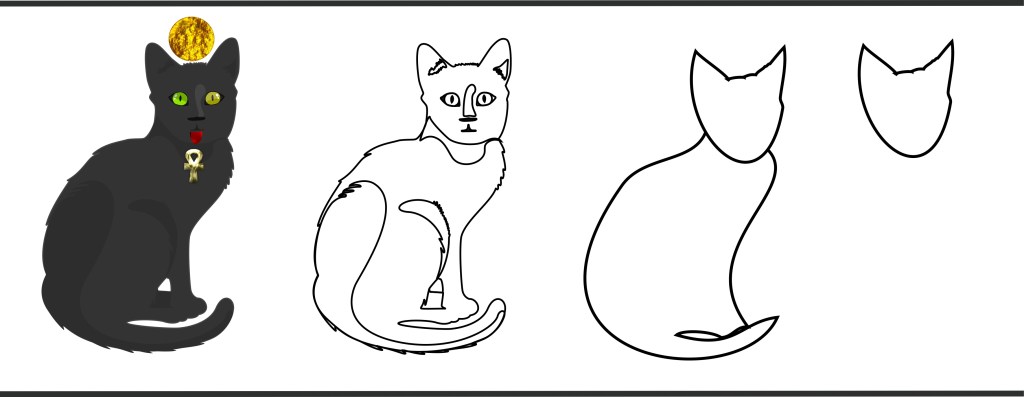
Écrire en dessinant ? Rien de plus facile !
L’écriture Hiéroglyphique est, pour une bonne part, la constitution d’un message sous la forme de rébus, des successions de graphismes expriment les objets, les personnes, les animaux, la flore, les situations.
Les traits, les formes, les dessins ne sont que rarement les choses représentées mais leurs prononciations. Celles-ci sont conditionnées par des signes de ponctuation.
En dessinant, il est possible de mélanger les graphismes explicites et non explicites, tels que des représentations de divinités avec des signes triviaux, indicatifs de sens.
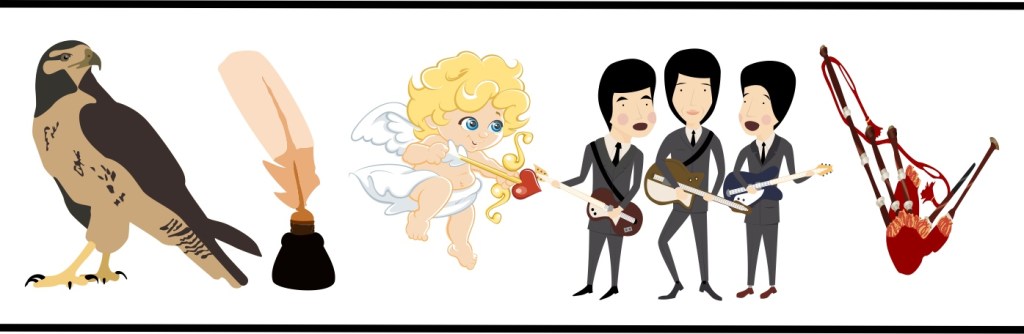
Ainsi, si l’on fait figurer une image d’oiseau, un faucon, l’emblème de Rà, cela peut vouloir dire beaucoup de choses.
Faucon, écrire, romance, groupe, cornemuse.
Cela se lit de gauche à droite car le faucon regarde vers la droite. A priori, c’est facile à comprendre : un producteur veut travailler sur une chanson d’amour avec son parolier, tout en lui précisant habilement que les interprètes sont des guitaristes. Ici, les syllabes de « faucon » sont utilisées pour leurs sonorités et non leurs sens graphiques, il faut les entendre pour comprendre, ce qui est assez facile.
Et pour la cornemuse ? Est-elle présente parce que les guitaristes sont de Glasgow ?
Là où cela se complique.
On lira dans ce cas : Faut qu’on écrive de l’amour pour le trio des chanteurs Écossais. Toutefois, la cornemuse peut aussi être là pour ses sonorités. Il convient de remplacer Écossais par la performance vocale du trio
On comprend : Faut qu’on écrive une chanson d’amour pour les guitaristes qui couinent. L’auteur du message considère qu’ils chantent trop haut.
Comme si cela ne suffisait pas, une autre interprétation se propose, celle qui implique la nature de la cornemuse, dans laquelle on souffle afin de la presser pour en faire sortir l’air.
Le sens est alors quelque peu différent : Faut qu’on écrive une chanson d’amour pour ce trio qui me gonfle et me pressure.
Le rédacteur exprime son agacement envers ses musiciens, très insistants et dont le montant du cachet lui semble exagéré. Ce qui induit que c’est bien un producteur qui écrit.
On ne peut pas exclure que les trois sens se superposent, les musiciens sont Écossais, près de leurs sous, avides de nouveaux succès et chantent dans les aiguës.
Le recours aux noms d’oiseaux.
L’interprétation des hiéroglyphes n’est pas toujours facile. Aussi, il est important d’ajouter des indicateurs de compréhension.
Dès que l’on ponctue le faucon avec un canard, nous savons qu’il s’agit d’un nom d’oiseau.
Ce second message se lit de droite à gauche : bouleau, faucon sur canard, épouvantail, mésanges sur canard.
Le message signifie que le boulot du faucon, on comprend que l’oiseau est évoqué grâce à la ponctuation palmipède, est de faire peur aux indésirables, lesquels sont des oiseaux, ce que l’on déchiffre de nouveau grâce au volatile à col-vert.
Merci doublement au canard qui, au passage, survit au faucon.
Nous percevons pourquoi le hiéroglyphique est resté longtemps incompris. Sa logique est intelligible certes, à la condition expresse de souscrire à son côté élastique.
L’immense avantage de cette approche graphique est qu’elle garantit à celles et ceux qui la pratiquent une paix royale sur leur choix, mais non sur leur orthographe.
À tel point que règne, sur quelques milliers d’années, ce qui nous semble être la fantaisie la plus grande. Les signes se lisent de droite à gauche, ou de gauche à droite, les lignes verticalement ou horizontalement, en fonction de la place disponible pour compléter une phrase.
Toutes les configurations se rencontrent au fil des quatre mille ans d’usage de l’écriture documentée et tourmentée de l’Égypte.
Et comme si cela n’était pas assez déroutant.
Durant sa longue histoire, tour à tour État en formation, pays constitué, Empire agressif ou territoire conquis, l’Égypte a connu guerres, invasions et occupations, par des peuples et des dirigeants qui n’étaient pas tous d’origine Nil contrôlée.
Au fil des besoins politiques, les déclarations que l’on croyait définitives, les patronymes de dirigeants, les hauts faits, les orientations religieuses, dévotions et filiations, furent retouchés, modifiés, expurgés ou effacés.
Imaginons, un instant, une époque technologique qui se verrait submergée de photos arrangées, de registres amendés, de citations hors contexte et de messages tronqués. Il serait difficile, quelques siècles plus tard de démêler le clairement faux du volontairement mensonger !
Les premières dynasties connaissent une forte croissance de leur influence politique qui s’accompagne de celle de leur administration, indispensable pour gérer un pays qui s’étend au fil des conquêtes le long du Nil et un peu vers l’Est.
Faire dans le grandiose et l’éternel est un impératif mystique, mais c’est lent et cher.
Faire dans le pratique et le souple devient un impératif économique.